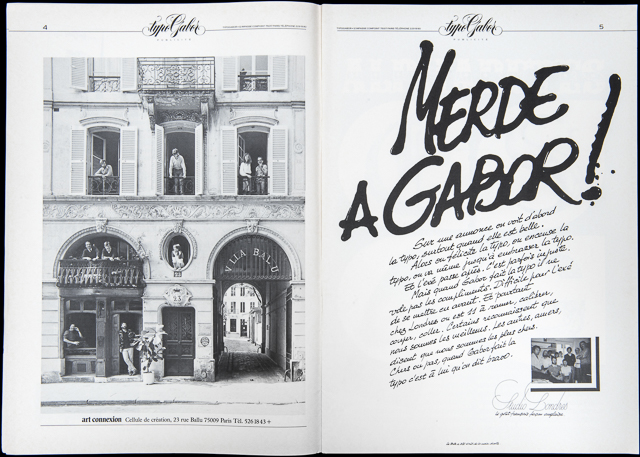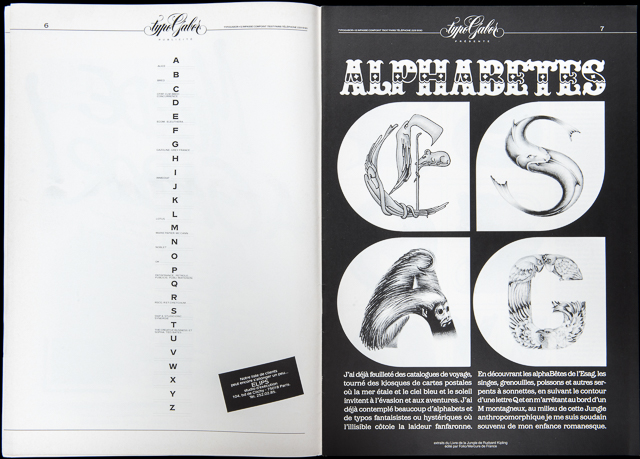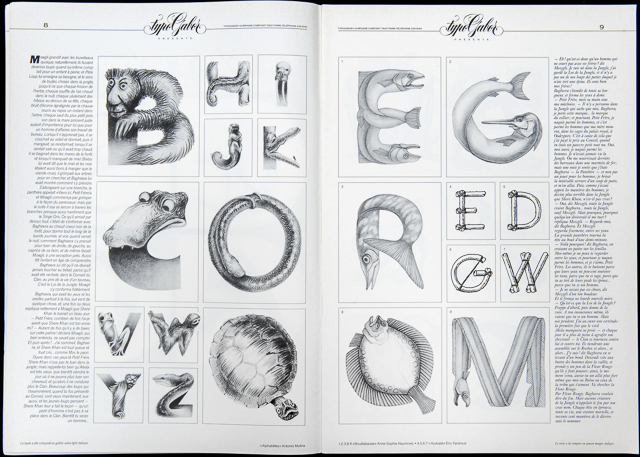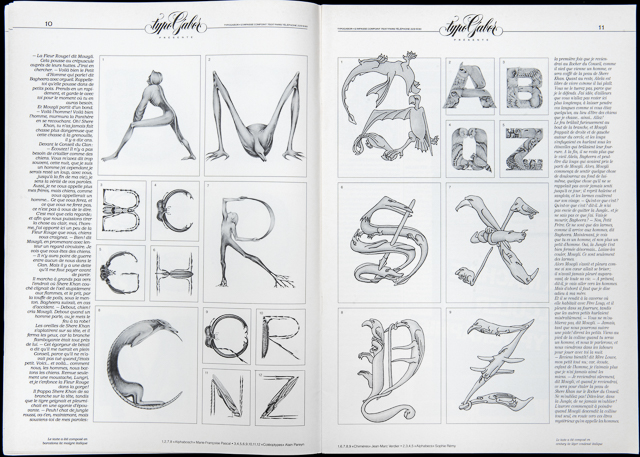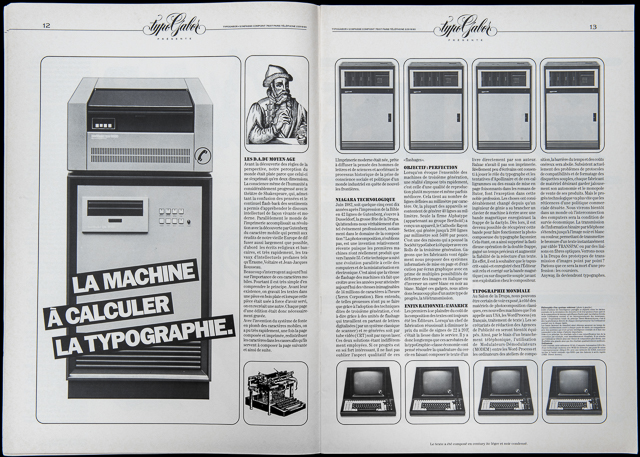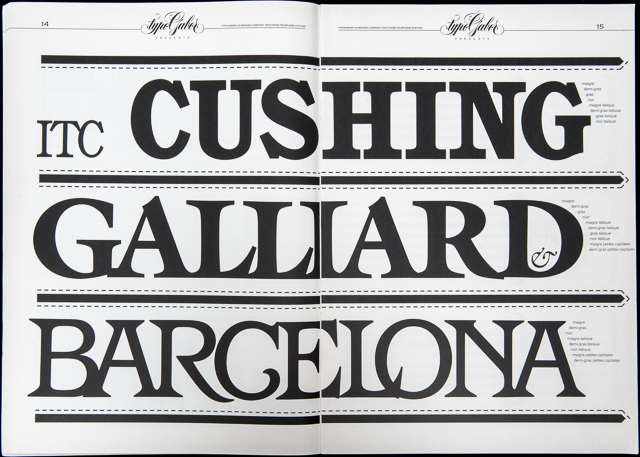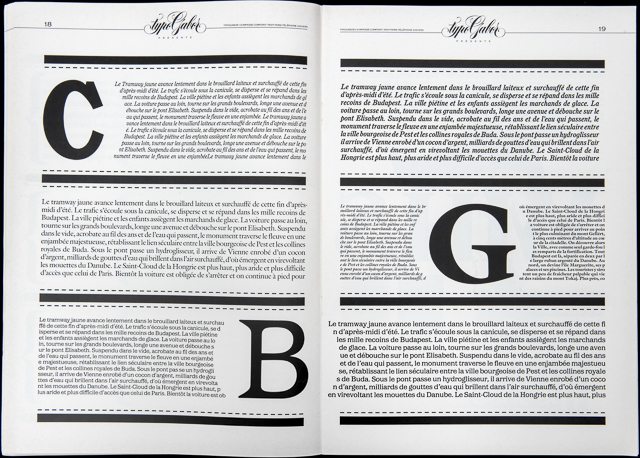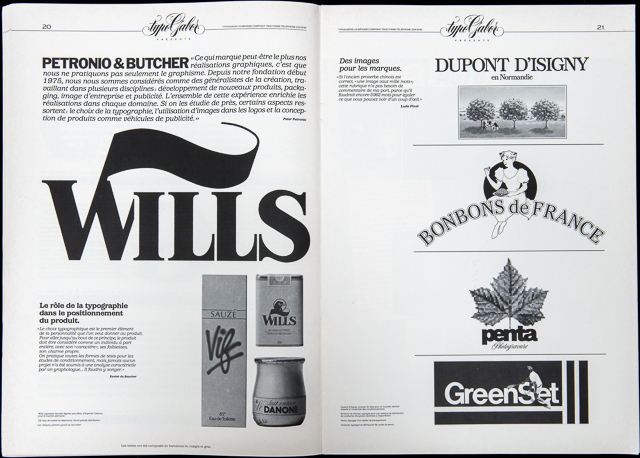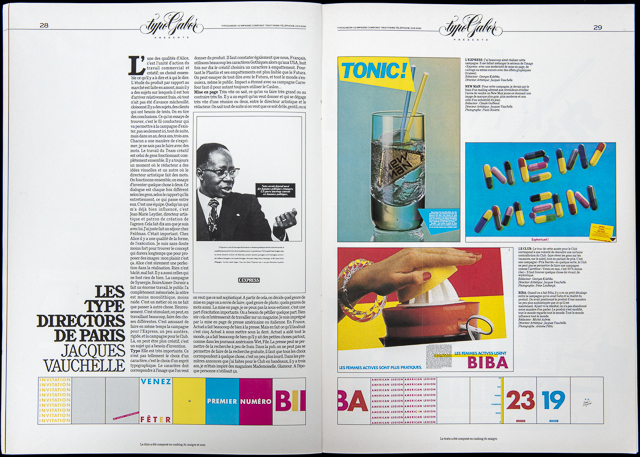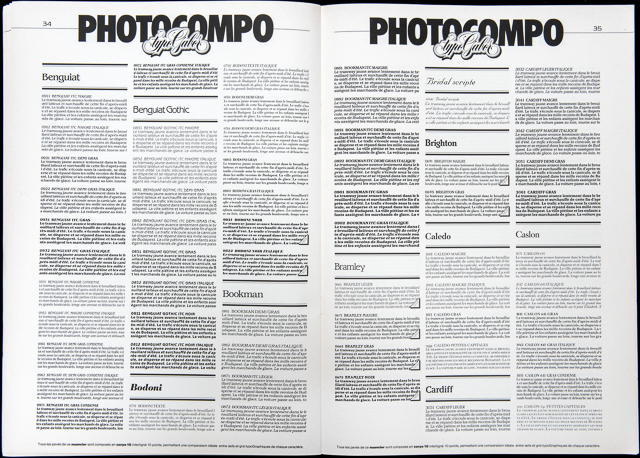
l’Histoire des Magazines typoGabor N°5 | Les TypeDirectors
« TypoGabor présente » N°5 | Les TypeDirectors
Même si certaines manifestations graphiques sont en germe dès 1968, typoGabor est fondée en 1973 par Paul et Peter Gabor. L’activité de la société est double : atelier de création graphique autour des clients historiques de Paul Gabor et société de services typographiques sous l’égide de Peter Gabor.
Les premières années de typoGabor sont rythmées par le fonctionnement coûteux et limité des Diatronic de Berthold. Tant et si bien qu’à la fin des années 1970, la continuité d’exploitation semble compromise. C’est à la faveur d’une annonce dans la revue CARACTÈRE que Peter Gabor découvre l’AlphaType. Il y voit l’amorce d’une révolution du digital. Ce sera son ami (depuis) Raymond Aubry, chef d’Atelier de Graphiservice à Bruxelles qui achèvera de le convaincre.
Un système de composition américain venant de Chicago, qui pour la première fois, propose non plus d’acheter mais de louer (prix dérisoire) des polices de caractères, ce qui porte l’offre et la diversité typographiques à un niveau inédit : 1 000 polices contre 80 sur Diatronic auxquels s’ajoutent 16 polices supplémentaires tous les mois. « typoGabor présente » naît en 1980 de deux constats.
Il ne s’agit plus de faire de la Pub pour une entreprise, mais d’informer et d’éduquer un marché. La Publicité. Un marché où s’affrontaient une trentaine de concurrents proposant tous à peu près les mêmes services (24/24, coursiers, catalogues de calibrage gratuits et qualité de composition supérieure à celle de l’édition ou de la Presse). typoGabor connaît alors le succès.
Les Directeurs Artistiques affluent et les commandes doublent de volume en l’espace de 2 ans. Mais la formule marketing du magazine ne plaisait plus à Peter Gabor. Il y préféra une formule nouvelle autorisant toutes les expérimentations typographiques. Le magazine littéraire de typoGabor était né. Plusieurs directeurs artistiques vont se succéder dans les cuisines typographiques de la maison Gabor. Bill Butt, Jérôme Binda, Philippe Duriez et pour finir Paul Gabor qui revient en 89 par une magistrale œuvre consacré aux Droits de l’Homme. L’Âge d’Homme.
L’expérience de la photocomposition fut de courte durée. Le Postscript arrive sous la forme commercialisée d’Adobe Type Manager et tous les prestataires de composition perdent 50 clients par jour à partir de 1990. Peter Gabor tenta encore d’adapter son entreprise en devenant le premier compositeur qui a basculé la totalité de son fonds sur Macintosh. Mais les dettes s’accumulant et victime d’un administrateur judiciaire peu scrupuleux, il finit par baisser les bras, non sans avoir personnellement créé 4 polices de caractères pour le Journal Libération en 1994.
Une aventure de vie passée à promouvoir la diversité et la qualité de composition, parce que comme l’aimait à rappeler son père Paul, d’après une phrase de Jean Cocteau : «Le style n’est pas une danse mais une démarche».
Couverture composée en Barcelona ITC. Cette couverture est l’une des plus étrange de toute la collection des magazines typoGabor Présente. De fait c’était un clin d’œil à la profession publicitaire. Il n’y avait pas de Type Director dans les Agences Parisiennes. À part Allison Girard qui travaillait (si ma mémoire ne me fait pas défaut) à la JWT, il n’y avait jamais eu de typeDirector en France. Et même aujourd’hui, encore, je n’en connais qu’un seul, Thomas Linard, de mes amis. Les raisons sont innombrables. La France n’a jamais privilégié la typoGraphie jusqu’à encore récemment. C’est sans doute les nouveaux outils du numérique, qui ont donné l’accès à la création typographique, sans plus être obligé de gratter de la carte, que les Directeurs Artistiques contemporains font assaut de créativité, soit en redessinant des typos, soit en les faisant redessiner par quelques studios spécialisés.
Les typothèques innombrables, les TypeKit d’Adobe, le foisonnement des fonderies indépendantes dans le monde entier ont libéré des énergies créatrices. Et puis il faut l’avouer, on a découvert assez tardivement le rôle prépondérant du signe en France. J’ose croire que dans les années 70 et 80 une société comme typoGabor s’est illustré précisément dans ce rôle de pédagogue et d’éducation du regard. Nombre d’écoles d’Art à l’époque ne s’occupaient guère de former l’acuité intellectuelle et visuelle aux formes typographiques et de la composition. La typoGraphie est un langage à part entière. Avec sa grammaire, sa syntaxe et son vocabulaire (de formes).
• Diriger une société de photocomposition et de phototitrage n’était pas une mince affaire. Passer de 0 salarié à 60 en l’espace de 17 ans. Un travail acharné de chaque jour. Rendu d’autant plus délicat que l’entreprise œuvrait jour et nuit. 24/24. Les problèmes techniques, de production et de choix commerciaux se posaient donc à un rythme quotidien qui s’étalait sur 24 heures. Un choix assumé. Mais l’on ne peut compter le nombre de nuits blanches que l’on peut y passer. C’était devenu une habitude, presque une routine. 5‑6 heures de sommeil quotidiens. C’est tout. Parfois un immense plaisir. Revenir à l’écriture. Les magazines me donnaient cette occasion que je n’aurais raté pour rien au monde.
• Et toujours le plaisir de mettre en avant le travail des étudiants en Arts Graphiques de l’ESAG/Penninghen où j’enseignais tous les samedis après mon mandat de la semaine.
• Ici un très article sur la situation des techniques en 1982. Vous pouvez cliquer sur la reproduction. Et re-cliquer pour zoomer sur le texte. Intéressante lecture pour comprendre les enjeux industriels d’une époque charnière où l’on commençait à recevoir des textes tapuscrits par des machines de traitement de textes. Plus besoin donc de re-saisir la dactylographie des textes. Ce fut une petite révolution pour les flux de production. Le Salon de la Bureautique, le Sicob se tenait chaque année pour présenter les nouveaux systèmes de traitement de textes. Nous sommes 2 an avant la naissance du Macintosh et Windows n’existait pas encore.